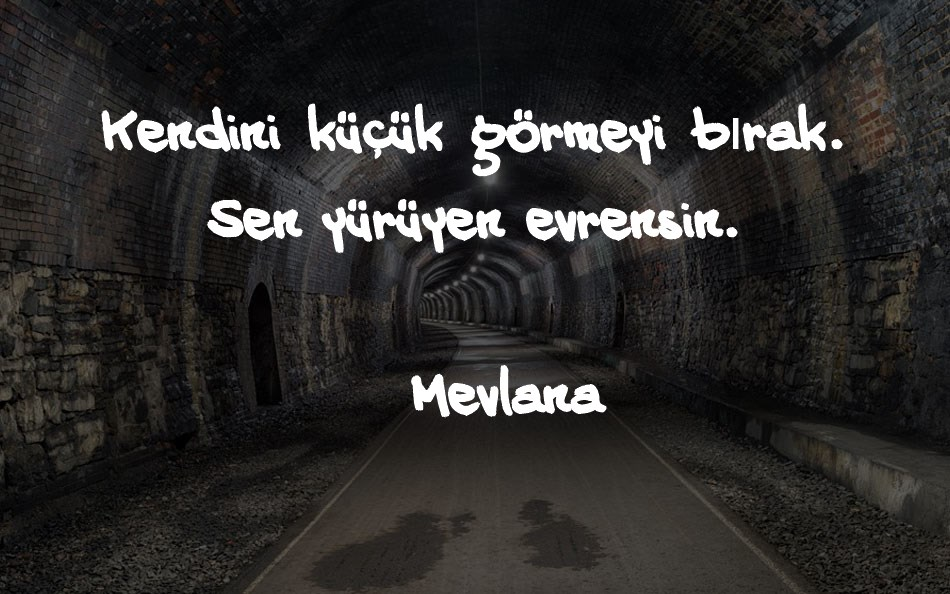
Sans serif ve el yazı stilleri kullandığınız veya hoşunuza giden, ücretli veya ücretsiz tüm font önerilerinize açığım.
Sans Serif kategorisinde Poppins tercih edebilirsiniz.
20 Cents
Cocogoose Pro Font Family
Intro Cond Font Family
Anke Font+Monoglyceride Font Family
Roboto Google font
Poppins dışında başka font olsa iyi olur yeniliklere açığım. Paralı da olabilir.
Brandon Grotesque isimli fontu tercih edebilirsiniz. Hem çağdaş hem italik kullanımlarda el yazısı şeklinde de kullanılabilir.
minion pro. bu arada bende coco goose yi beğendim.kanva da varmı acaba bu coco goose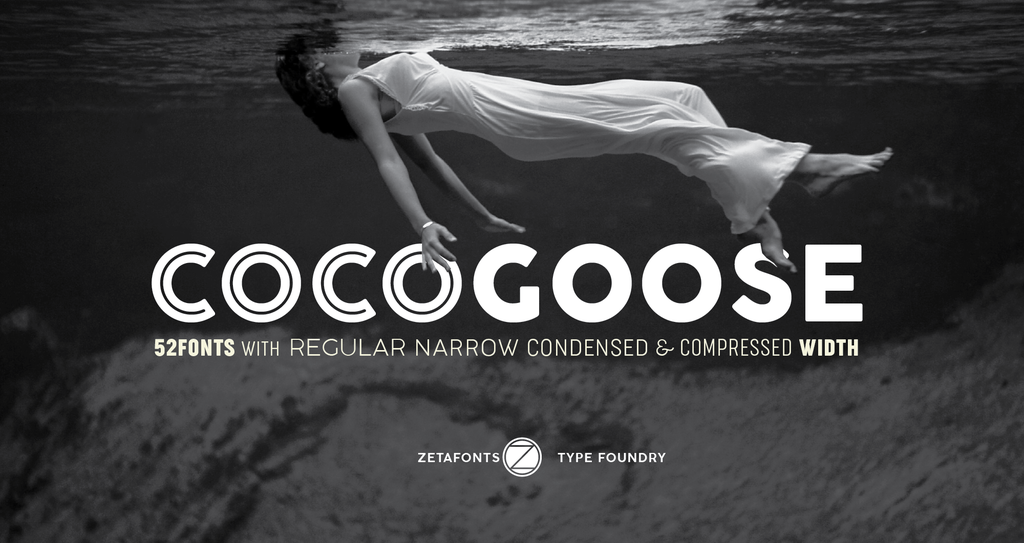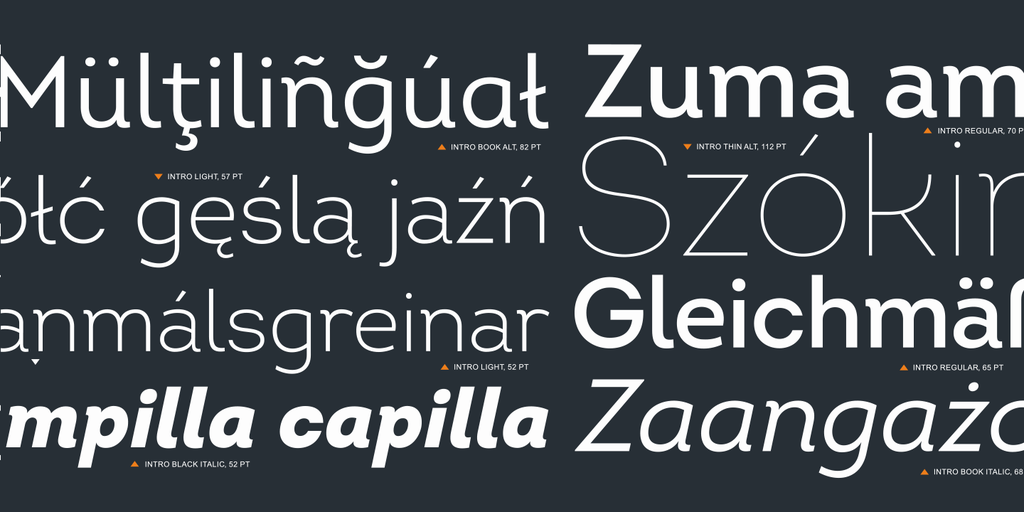